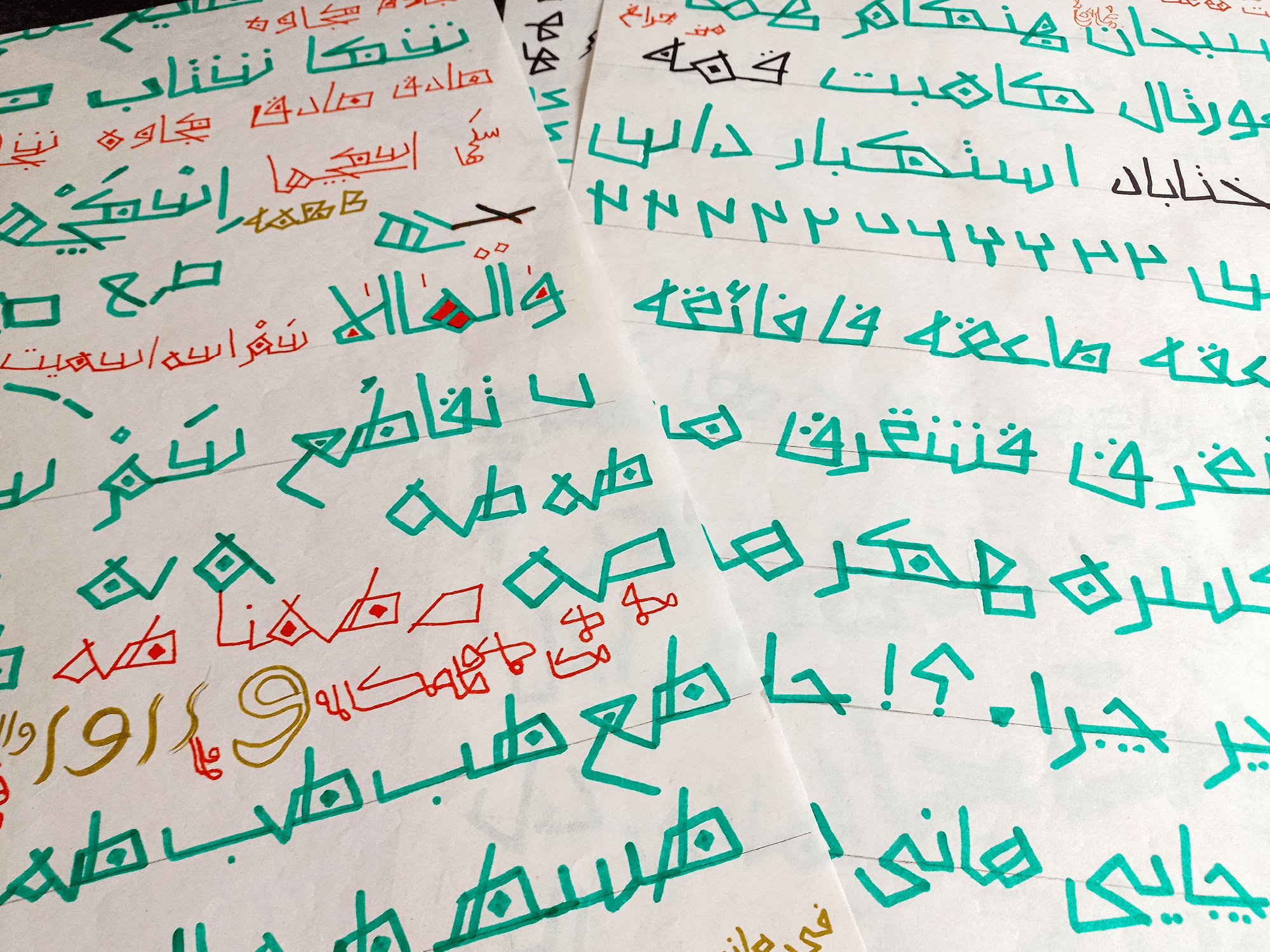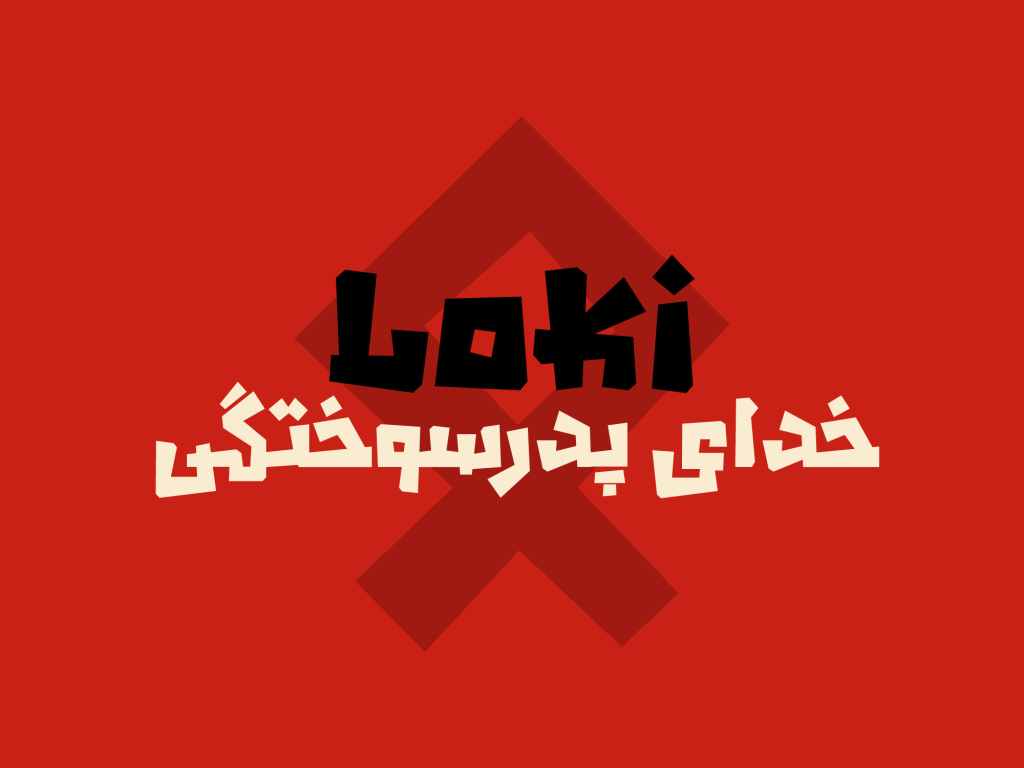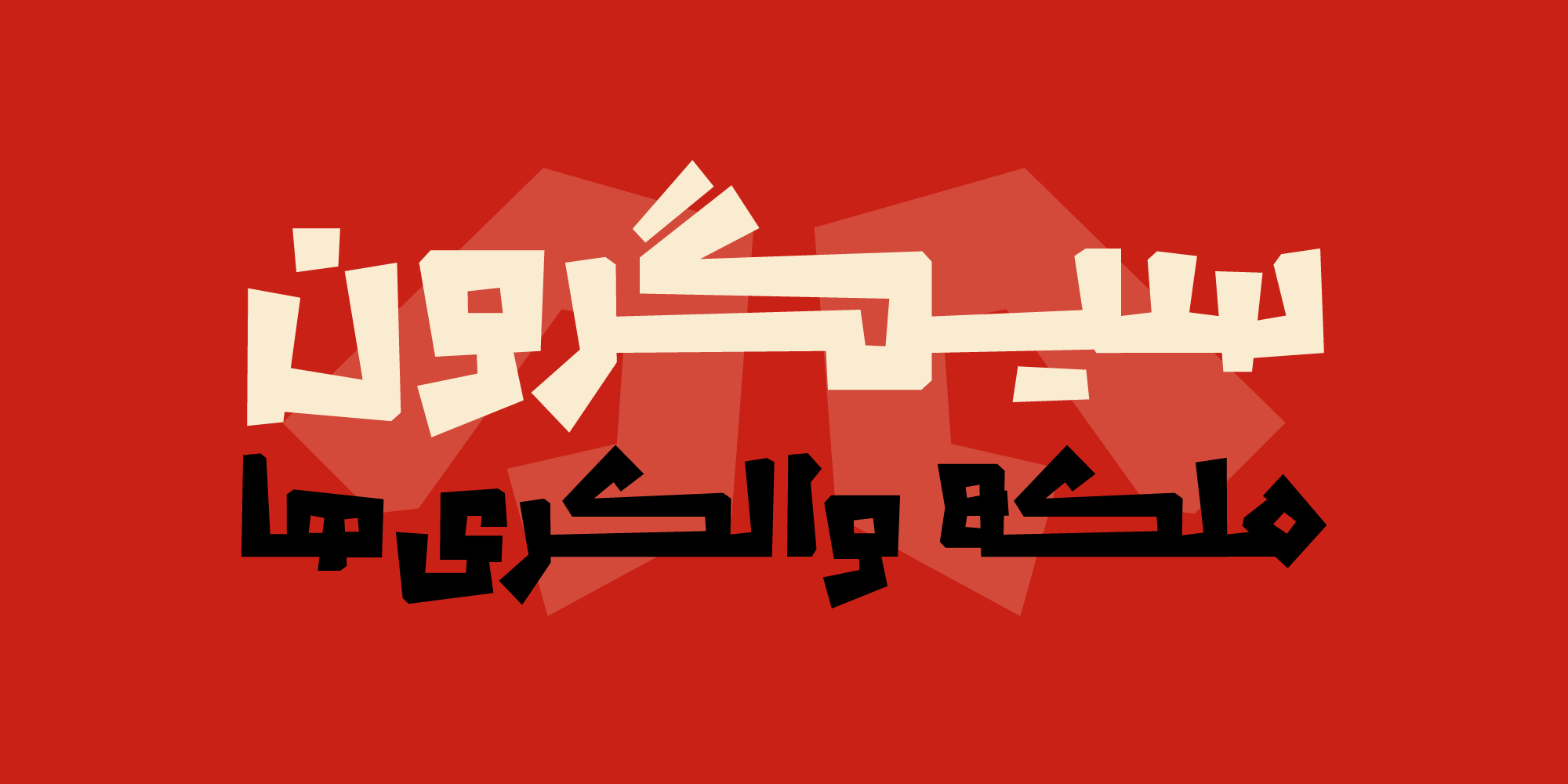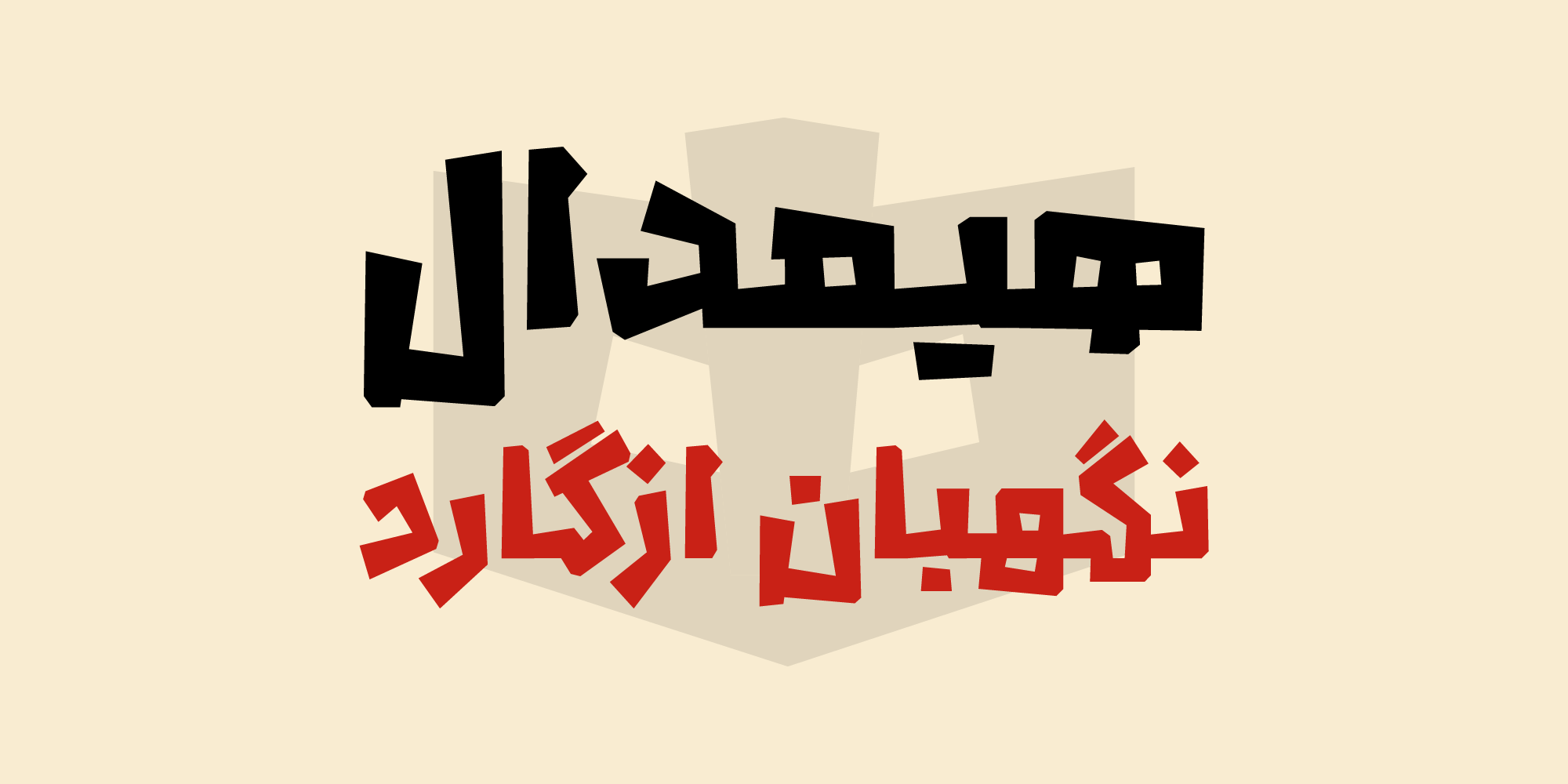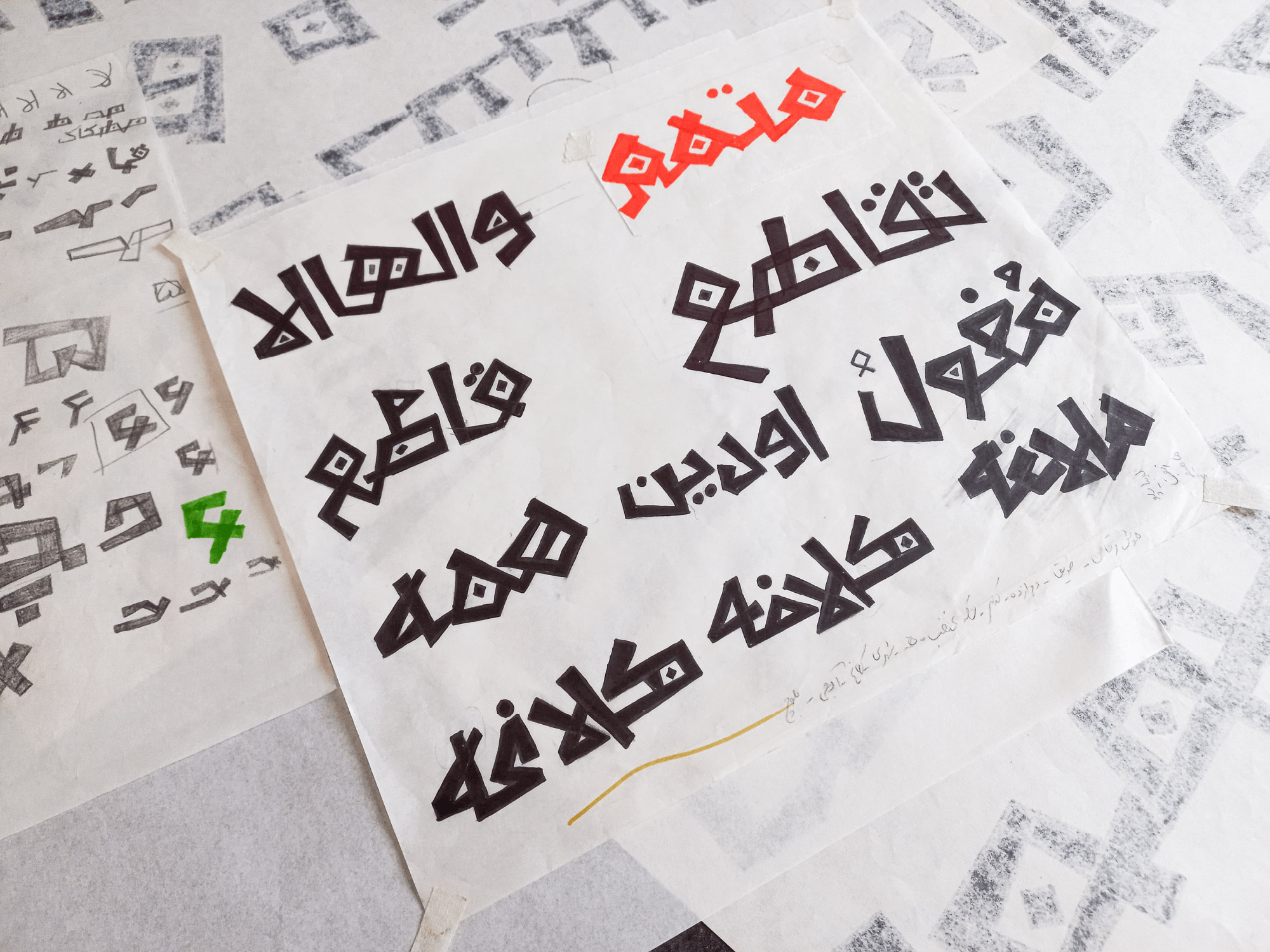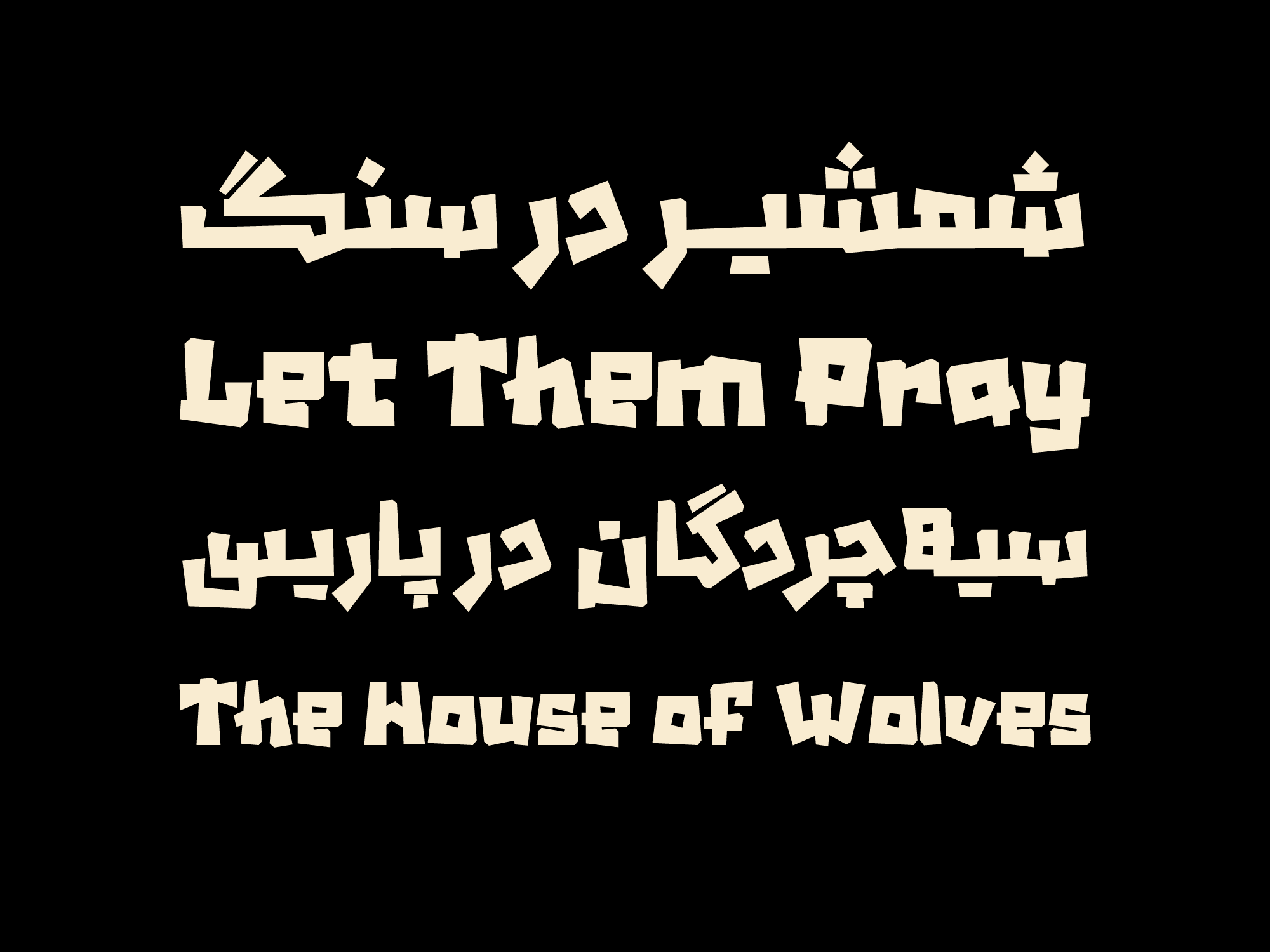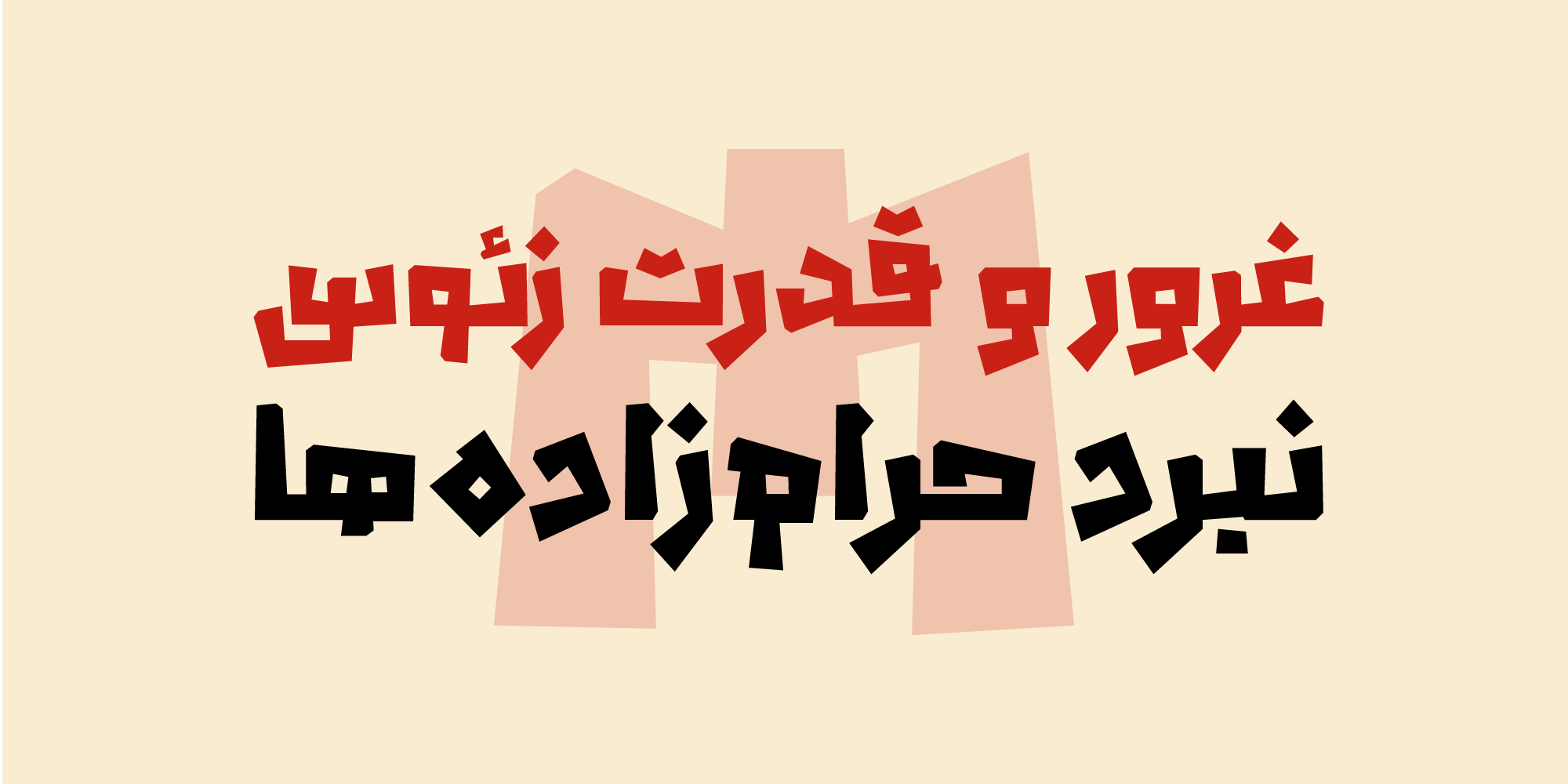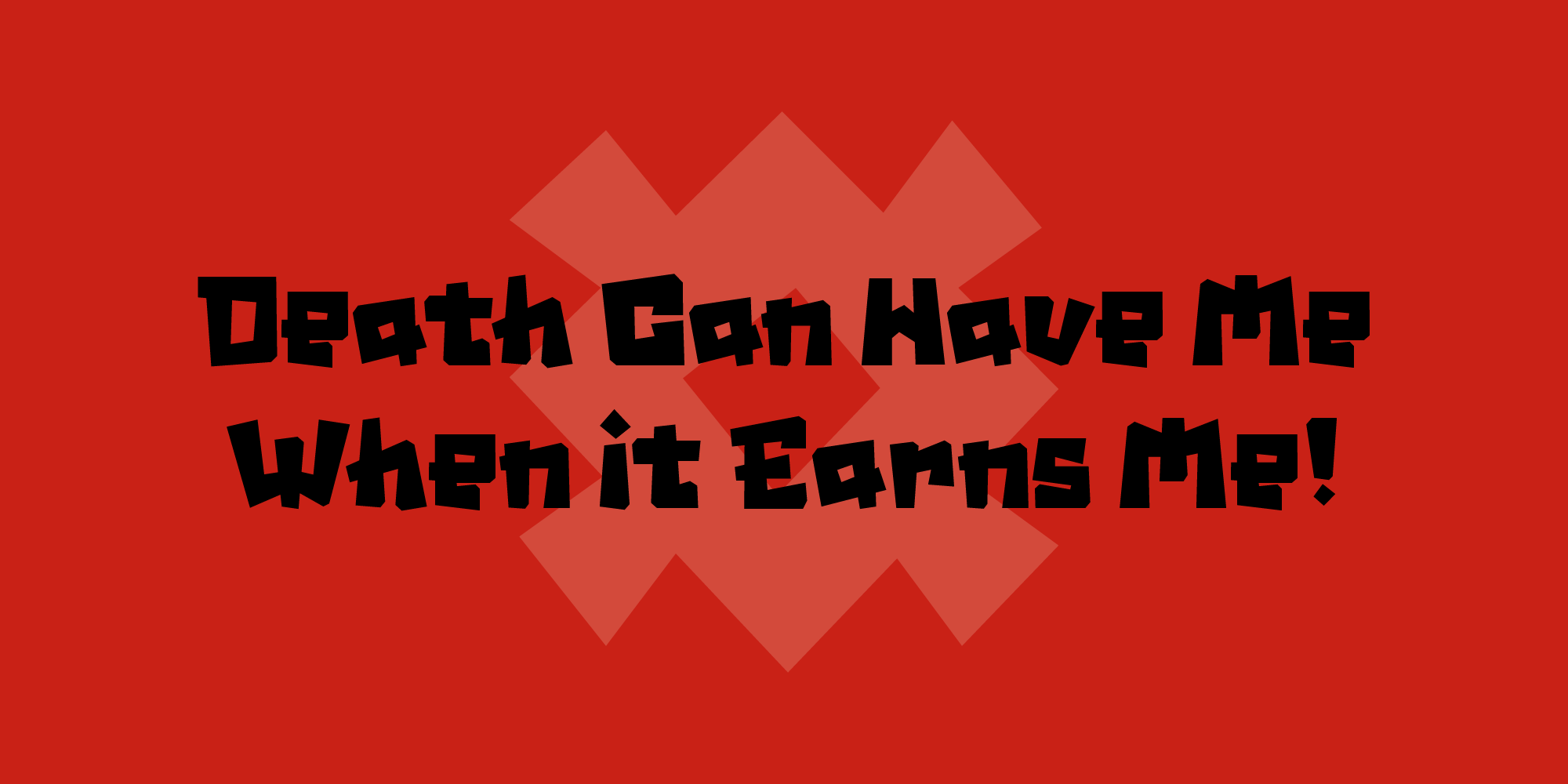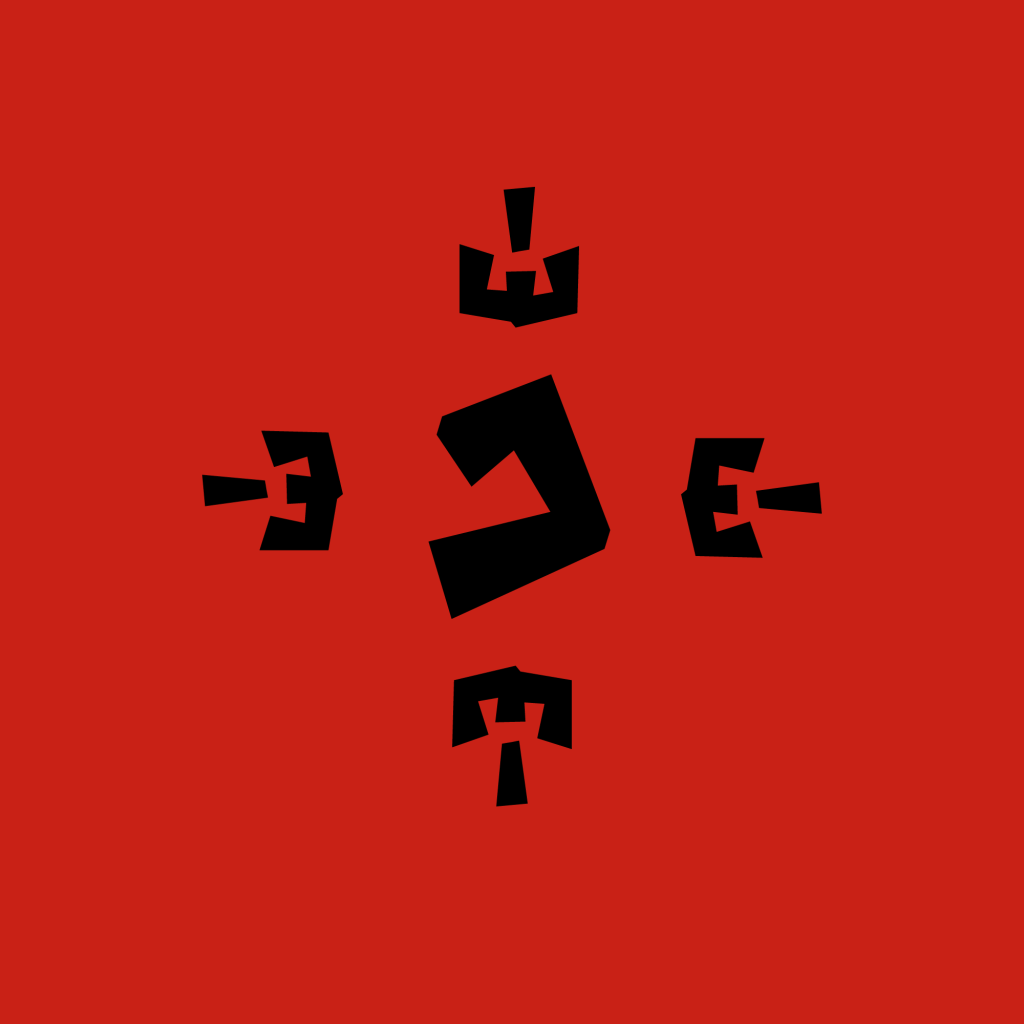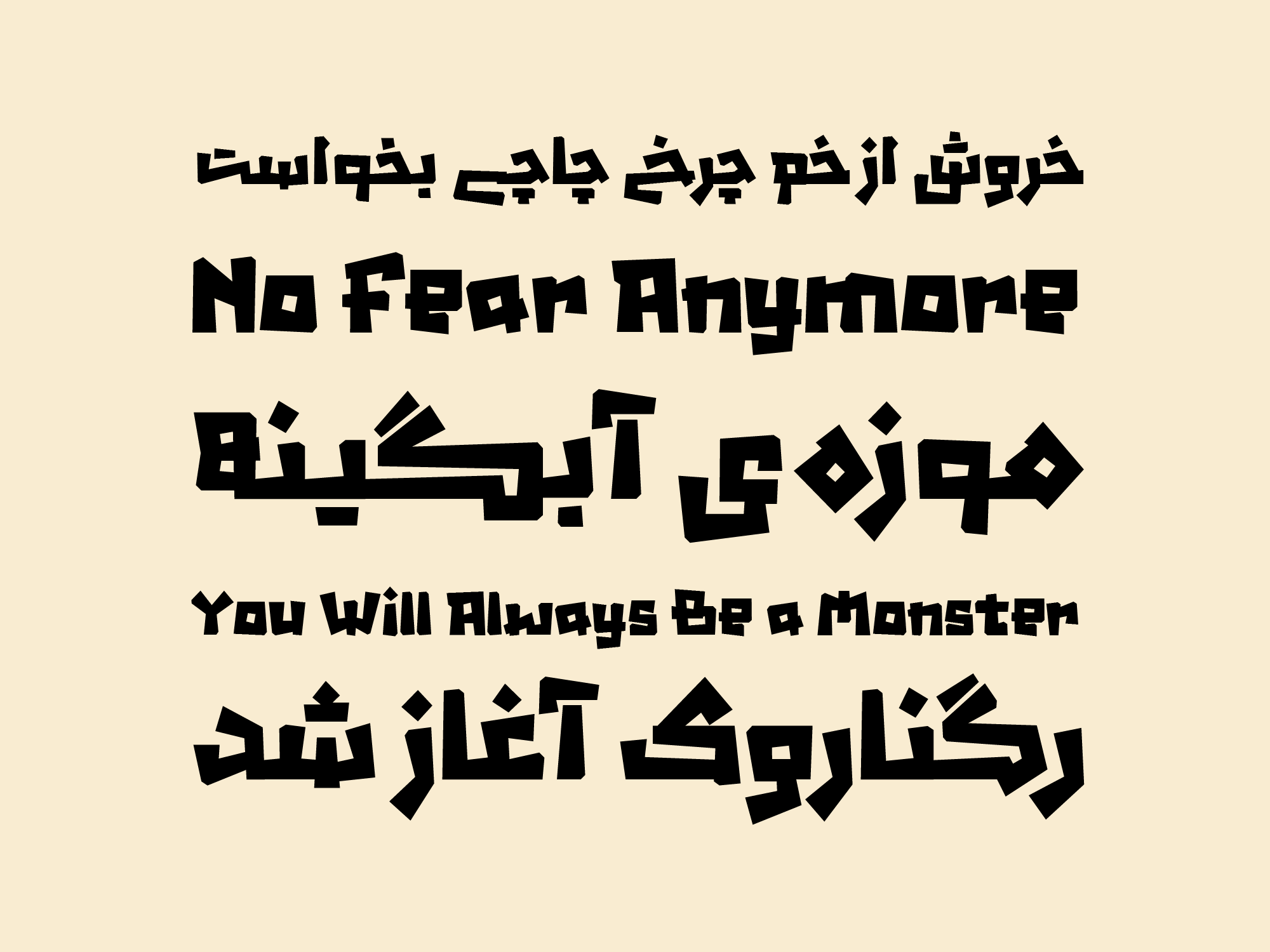
فونت والهالا قلمی بسیار نمایشی با رفتار و اتصال‌های عجیب و غریب است. الویت نخست آن خودنمایی و جذب نگاه ها به خود است و با فرم‌ها و رفتار‌های متفاوت حسابی جلب‌توجه می‌کند.
فونت والهالا قلمی نمایشی عصر کهن
فونت والهالا در نگاه اول قدری عجیب و غریب به نظر می رسد. در اصل هدف از طراحی این قلم دسترسی به فونتی با ویژگی نمایشی بالا جهت جذب نگاه ها به خود می باشد. قلمی برای تیتر ها و عناوین تبلیغاتی و محاوره ای از صنعت چاپ گرفته تا فضای وب و دیجیتال.
والهالا مسافری از عصر کهن
این تایپ فیس توسط امیرحسین رئوف از علاقه‌ی و ایده به دنیای اساطیر اسکاندیناوی شروع شد. والهالا همانطور که پر واضح است روحیه‌ی باستانی و بدوی دارد و از کتیبه‌های اسکاندیناوی استخراج شده است. یا به عبارت دیگر شخصیتی شبیه به یک وایکینگ دارد.
با کمی دقت می توانید به این نکته برسید که در مسیر طراحی این تایپ فیس اصلی ترین چالش و سختی در طراحی متفاوت همه‌ی حروف بایکدیگر، رفتارهای تصادفی و از همه‌ مهم‌تر تبدیل کردن چنین ویژگی‌هایی به یک فونت می باشد.
فرم های طراحی در این تایپ فیس از خطوط صاف و بدون انحنا تشکیل شده است. که هدف از این نوع طراحی ایجاد اشکال هندسی برای حروف و گلیف های ائم از شکستگی‌ها، تیزی‌ها، فرم‌های ابتدایی و عجیب و غریب، القای و انتقال حس باستانی و رمزآلود دنیای اساطیری اسکاندیناوی است.
همانطور که کاملا عیان است این تایپ فیس یک فونت نمایشی است؛ که در صورت نیاز به نمایش بیشتر حروف جایگزین و ترکیب‌ها امکانات بیشتری را برای این امر در اختیار کاربر قرار می دهند.